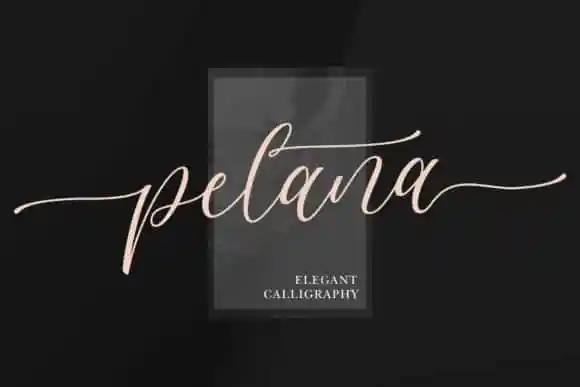
Pelana Calligraphy Font – Download Grátis
A Pelana Calligraphy Font é uma escolha perfeita para aqueles que buscam harmonia entre a sofisticação da antiguidade e a frescura contemporânea do design. Ela mantém os influentes traços de escrita chamigráfica enquanto se apresenta moderno e vivaz, sendo criada pelo font designer conhecido como Letteratom. Esta font é perfeita para aplicação em cartões de aniversário, cartões de agradecimento, citações, cartões de boas-vindas, logotipos, cartões de negócios e qualquer design que possa beneficiar da delicadeza dos traços humanizados. Além disso, sua PUA (Portable User Access) encerra-se para permitir acesso a todos os símbolos e cenas de maneira simples. A Pelana Calligraphy Font também traz uma variedade de linha do fundo, linhas suaves, belas formas e alternativas incríveis e impressionantes. Com essa fonte de letra à mão digital, você pode transformar seus designs em algo realmente único e atraente. Que tal adicionar um toque de personalidade a seu próximo projeto gráfico? A Pelana Calligraphy Font está aqui para fazer isso por você.